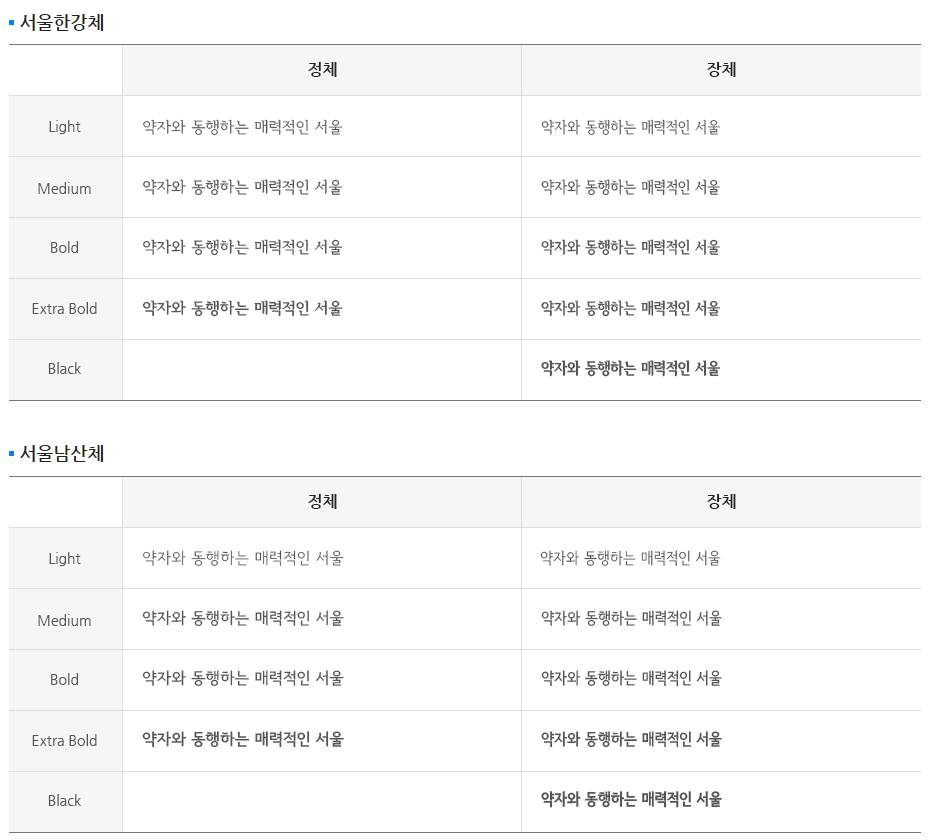
오늘부터 지자체에서 제공하는 무료 폰트 시리즈를 시작하려고 합니다. 지역적인 매력과 아이덴티티를 담은 각 폰트들은 지자체 브랜드를 대표하고, 지역사회와의 연결을 더할 수 있는 소중한 자산입니다. 각 지자체에서 제공하는 폰트들을 살펴보면서, 독특하고 매력적인 디자인 작업에 활용할 수 있는 폰트들을 소개하겠습니다.
서울서체
지자체 폰트 시리즈 1탄으로 서울시에서 제공하는 서울서체를 소개해드리려고 합니다.
서울서체는 강직한 선비정신과 단아한 여백을 담고 있으며 조형적으로는 한옥의 열림과 기와의 곡선미를 표현하였다고 합니다. 서체의 이름으로는 서울의 대표적인 자산인 '한강'과 '남산'을 응용한 서울서체는 우리민족 고유의 아름다운 언어인 한글의 문화적 자긍심을 더욱 높일 것이라고 합니다.
폰트 패밀리
서울서체의 폰트 패밀리에는 크게 '정체'와 '장체'가 있는데요, 정체의 장평(폰트 가로 넓이)이 장체의 장평보다 넓습니다. 그래서 정체를 사용했을 때보다, 장체를 사용했을 때 같은 공간에 더 많은 글자를 쓸 수 있습니다.
굵기는 각각 정체 4종, 장체 5종이 있습니다.
서울한강체와 서울남산체의 차이
'서울한강체'와 '서울남산체'는 돌기의 유무가 가장 큰 차이입니다. 돌기가 있는 '서울한강체'는 명조체/바탕체/세리프 폰트이고, 돌기가 없는 '서울남산체'는 고딕체/돋움체/산세리프 폰트입니다.